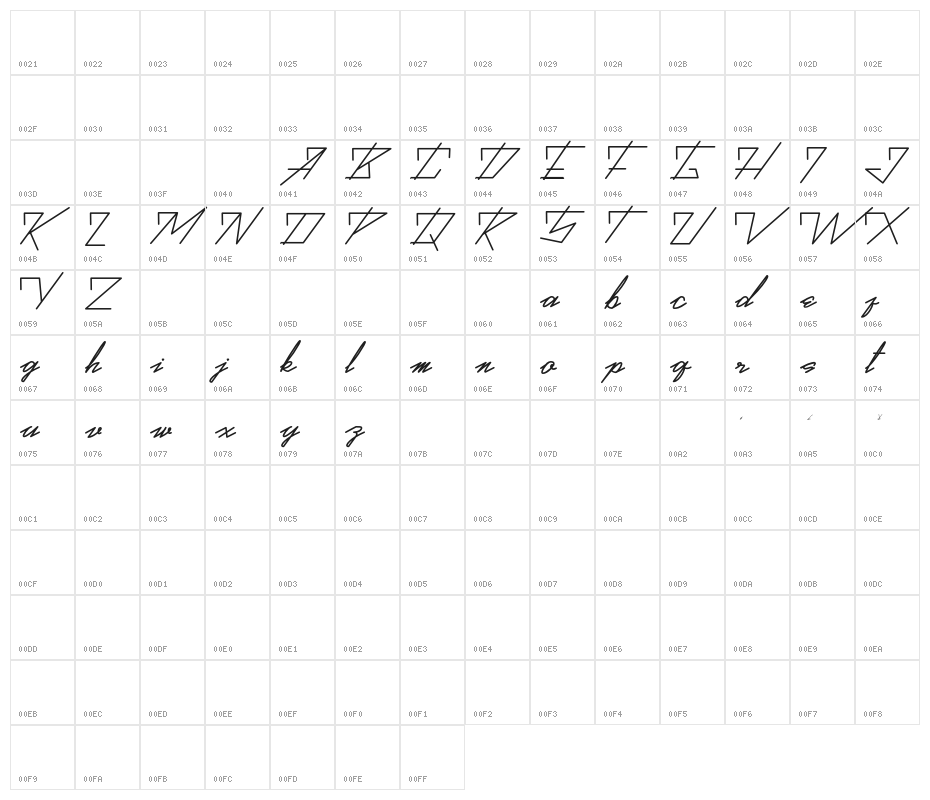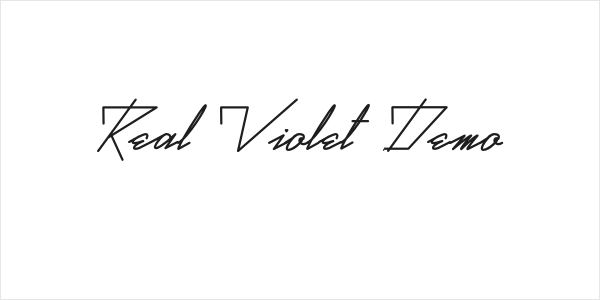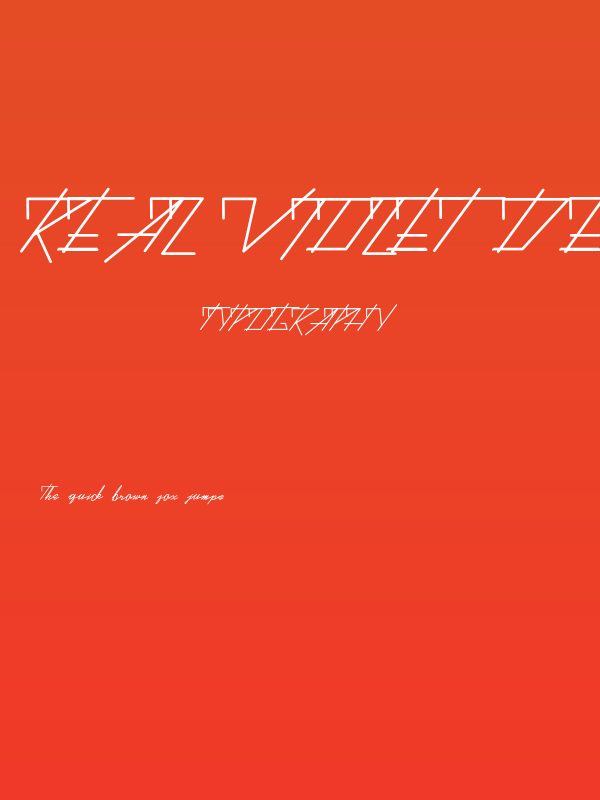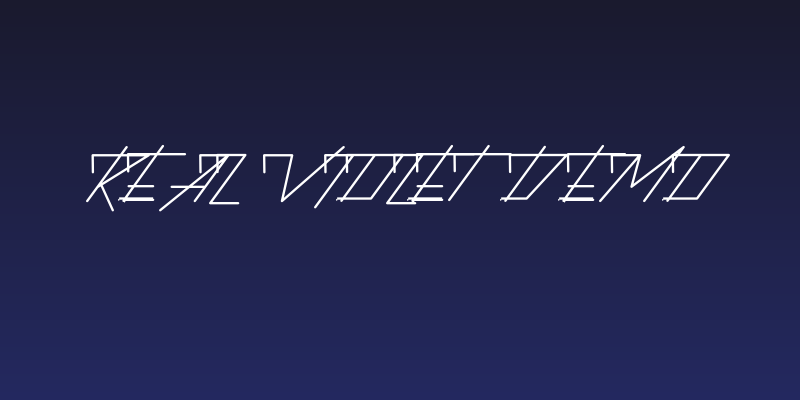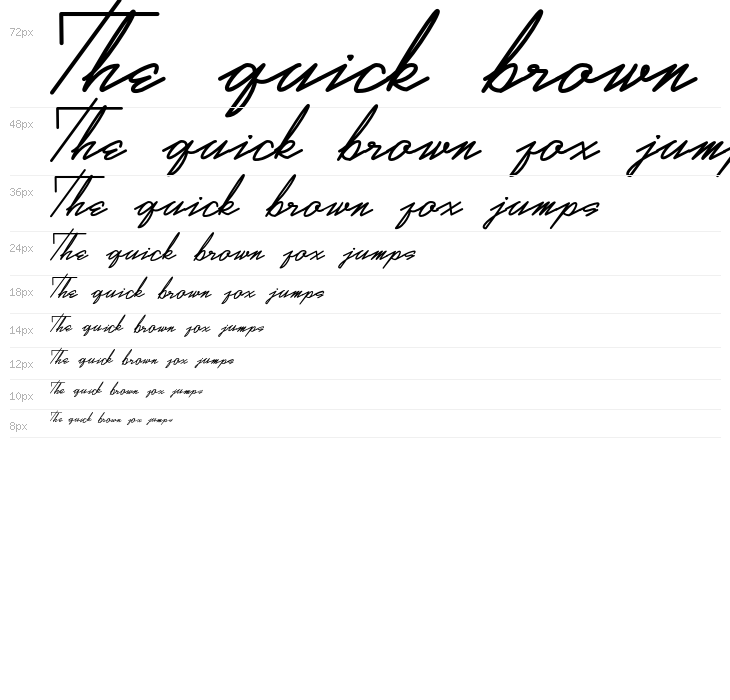
Real Violet Demo Font
| Caz de utilizare | Logos, Branding, Creative projects |
| Proiecte propuse | Ideal for branding, logos, and creative projects that require a mix of modern and classic aesthetics. |